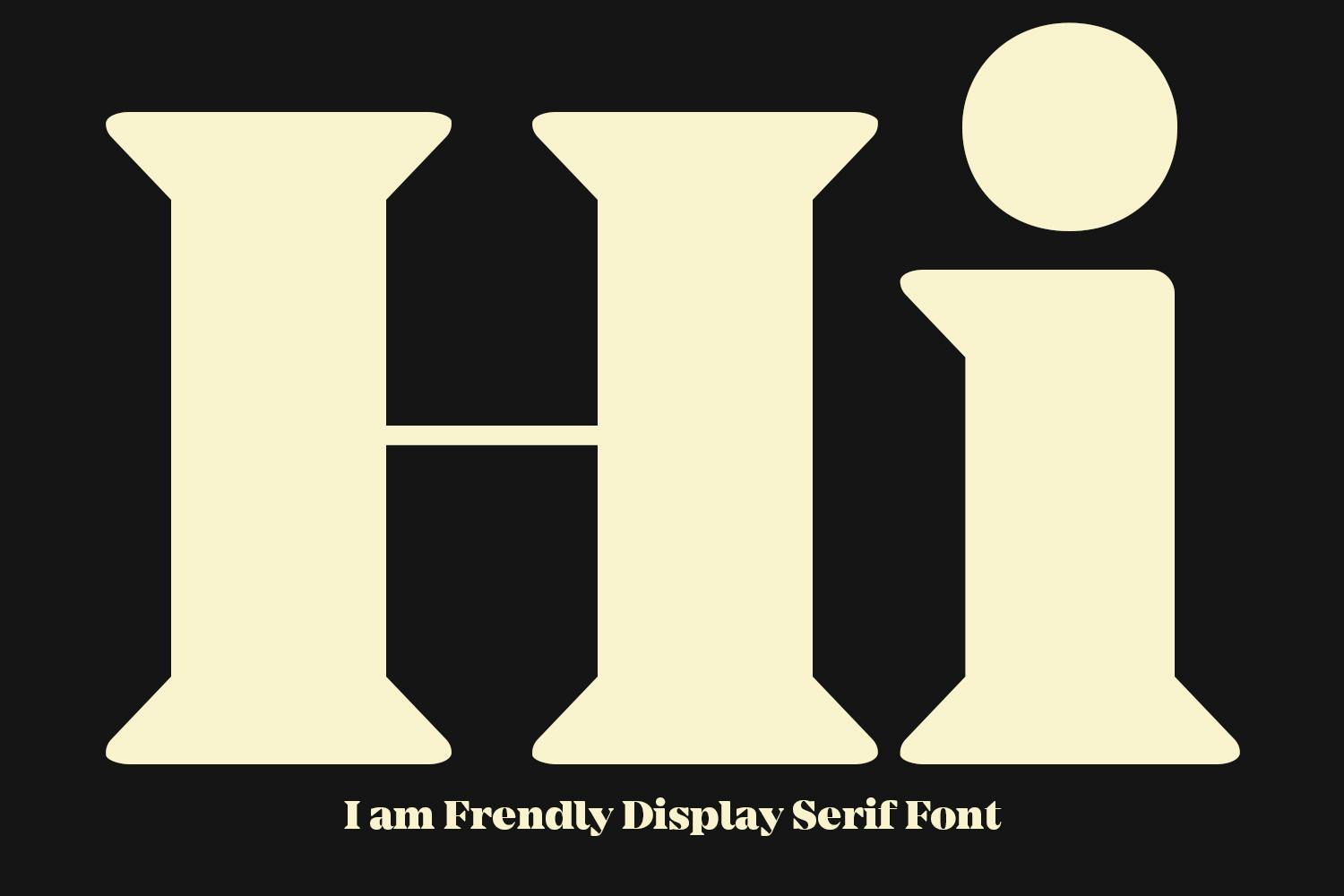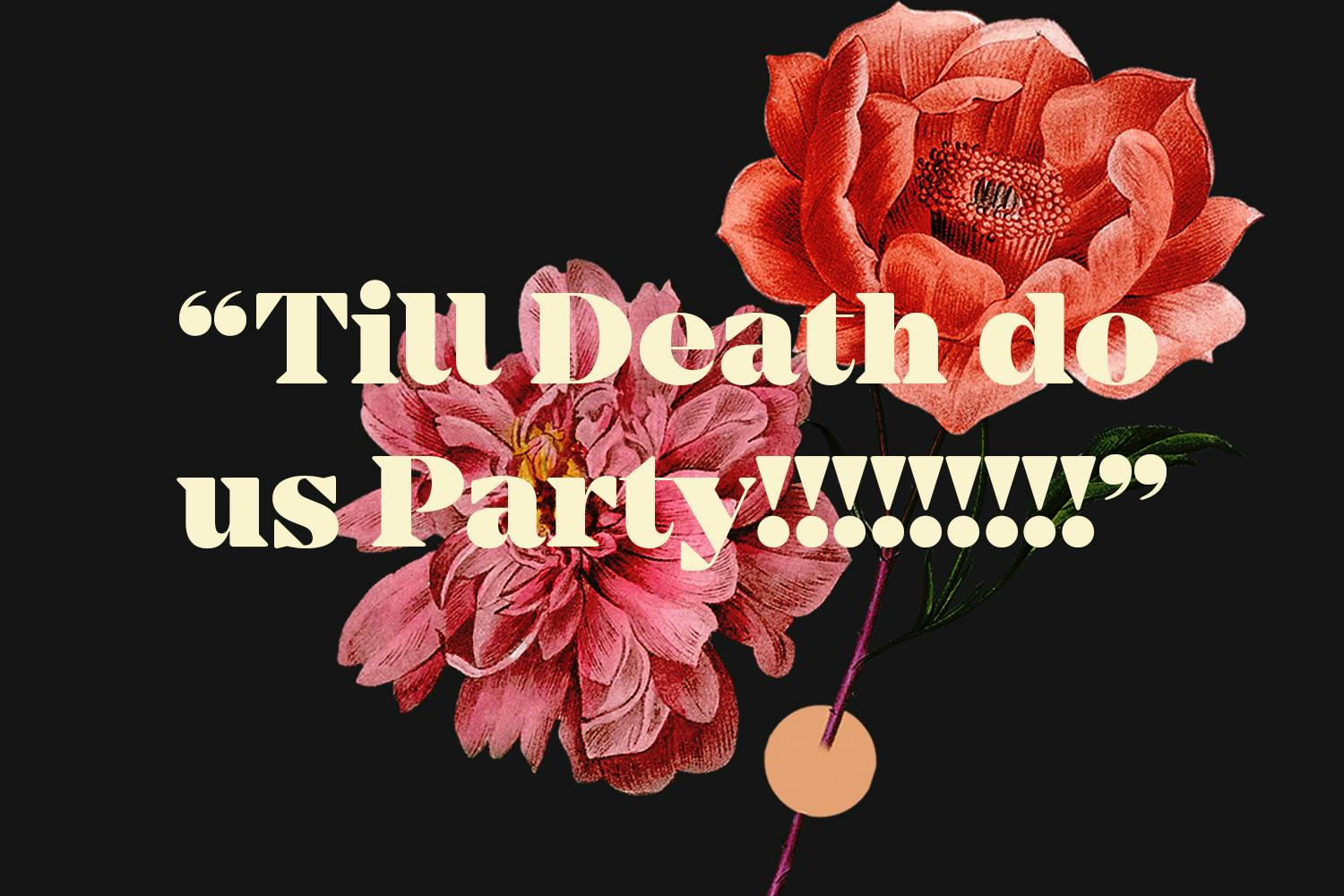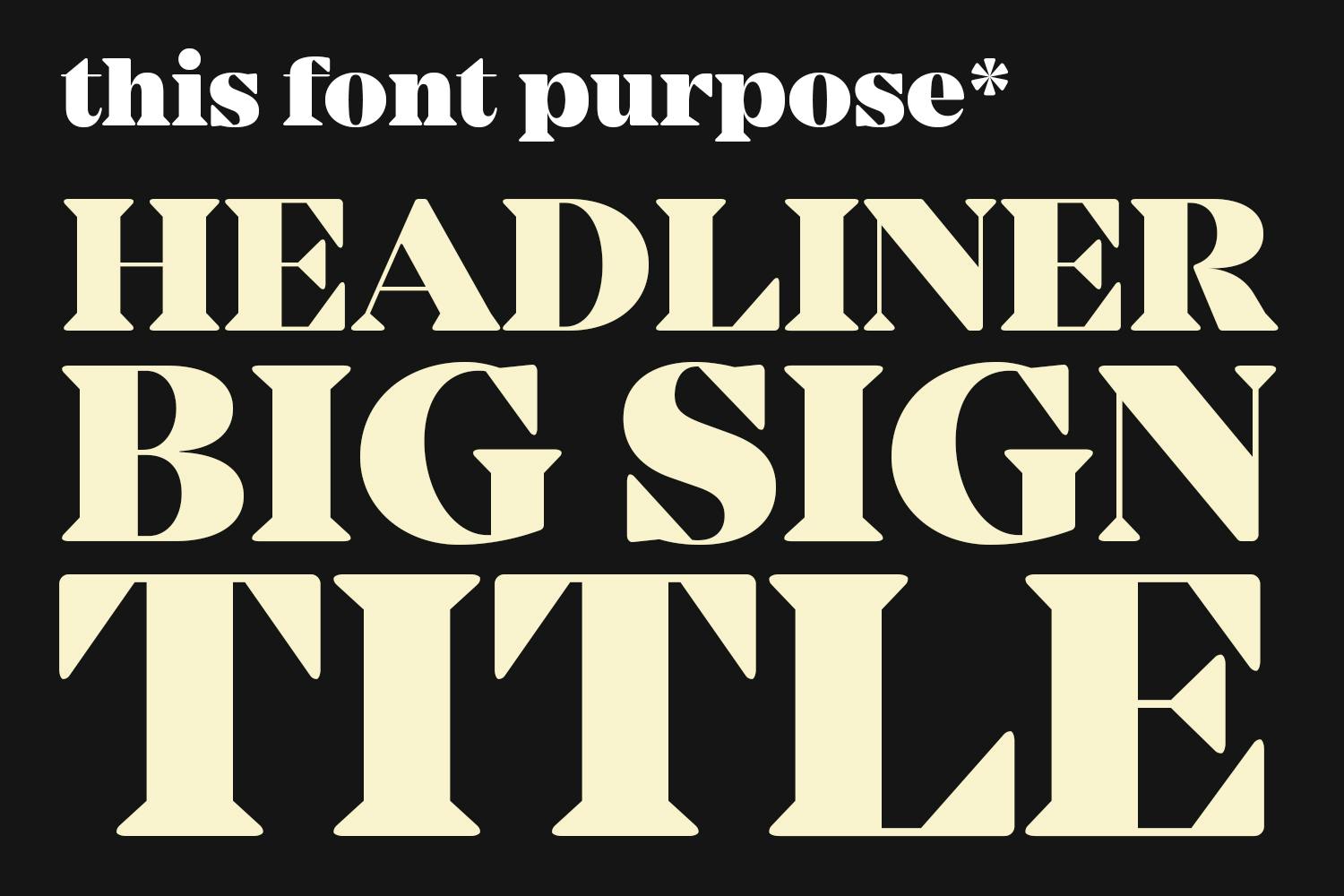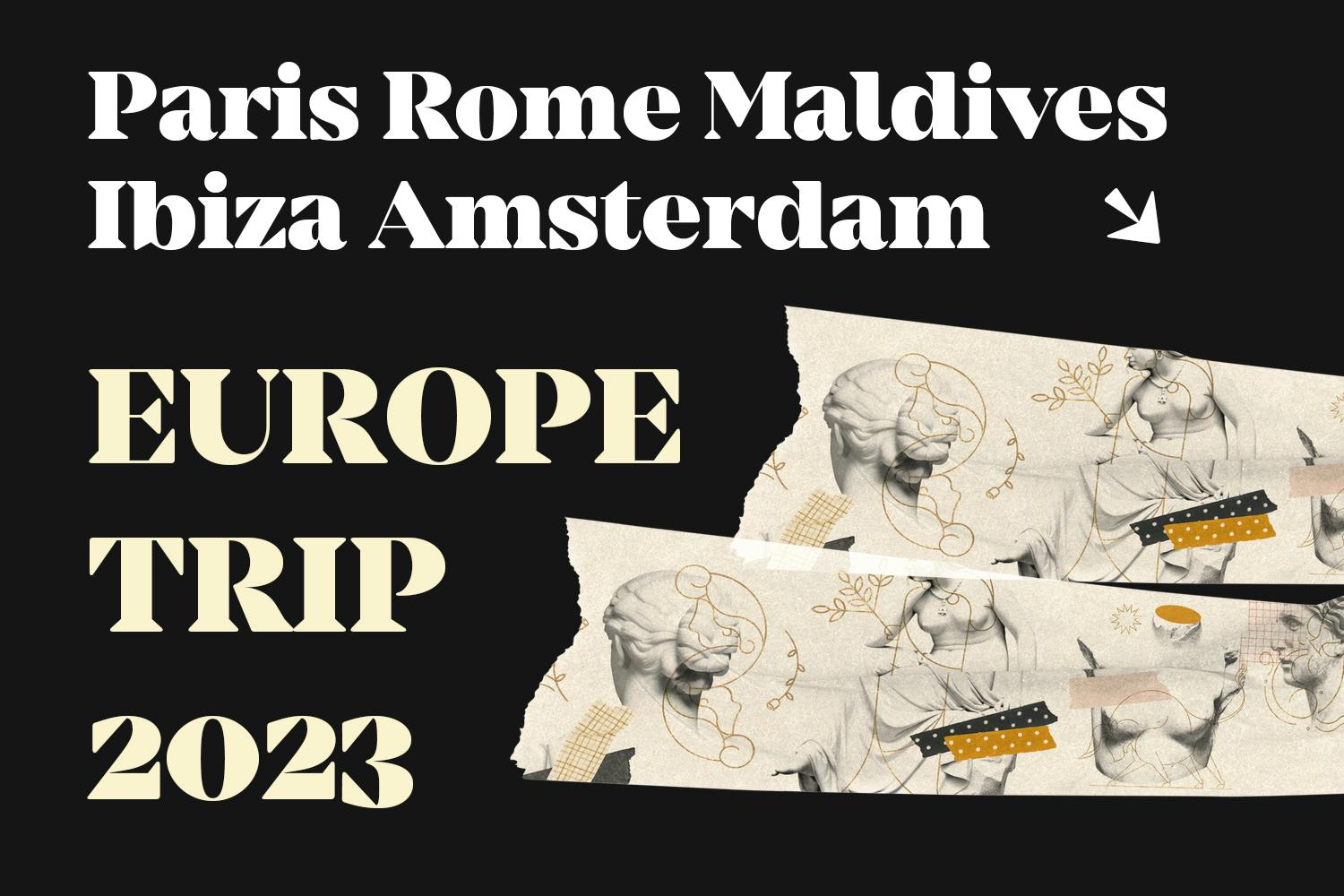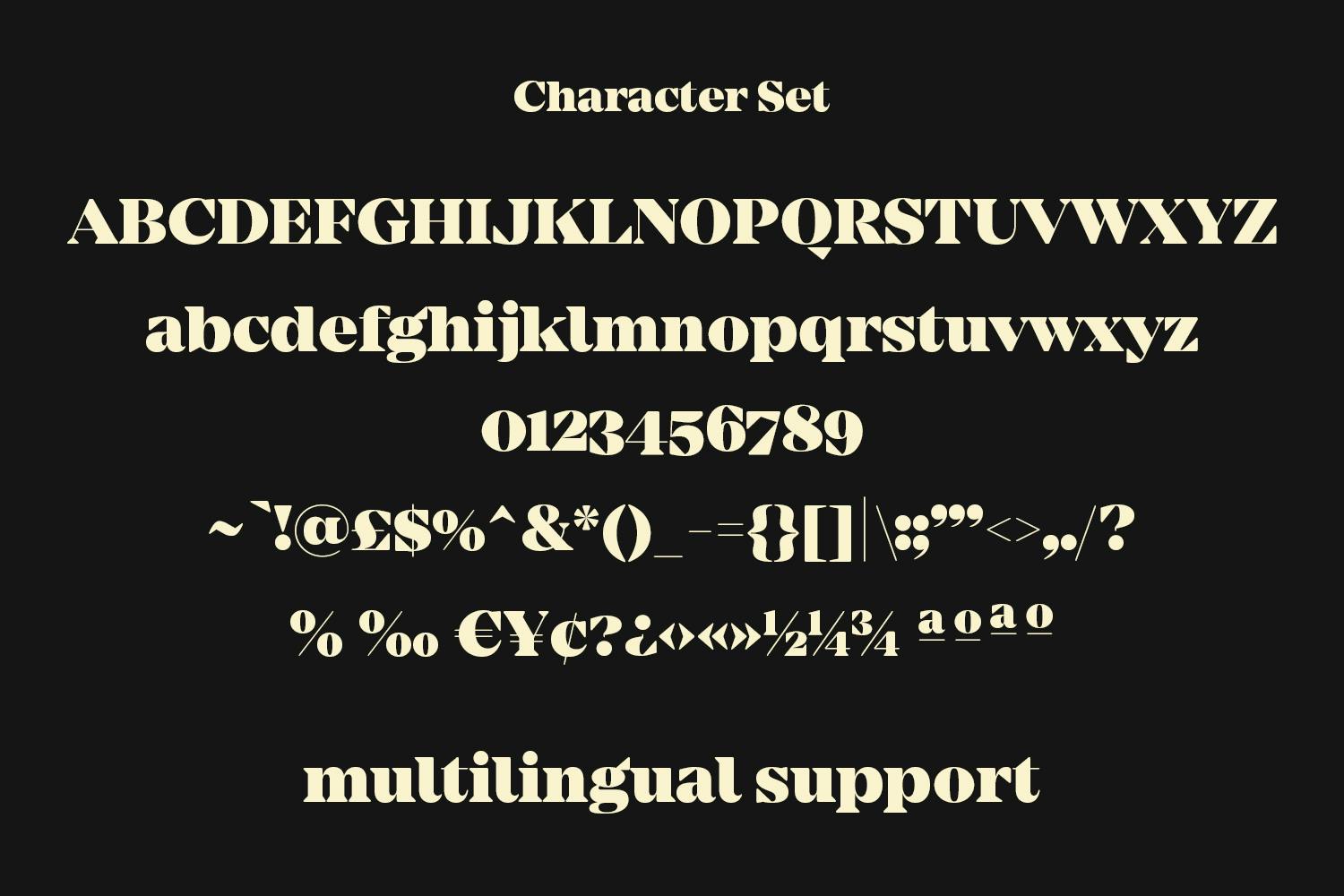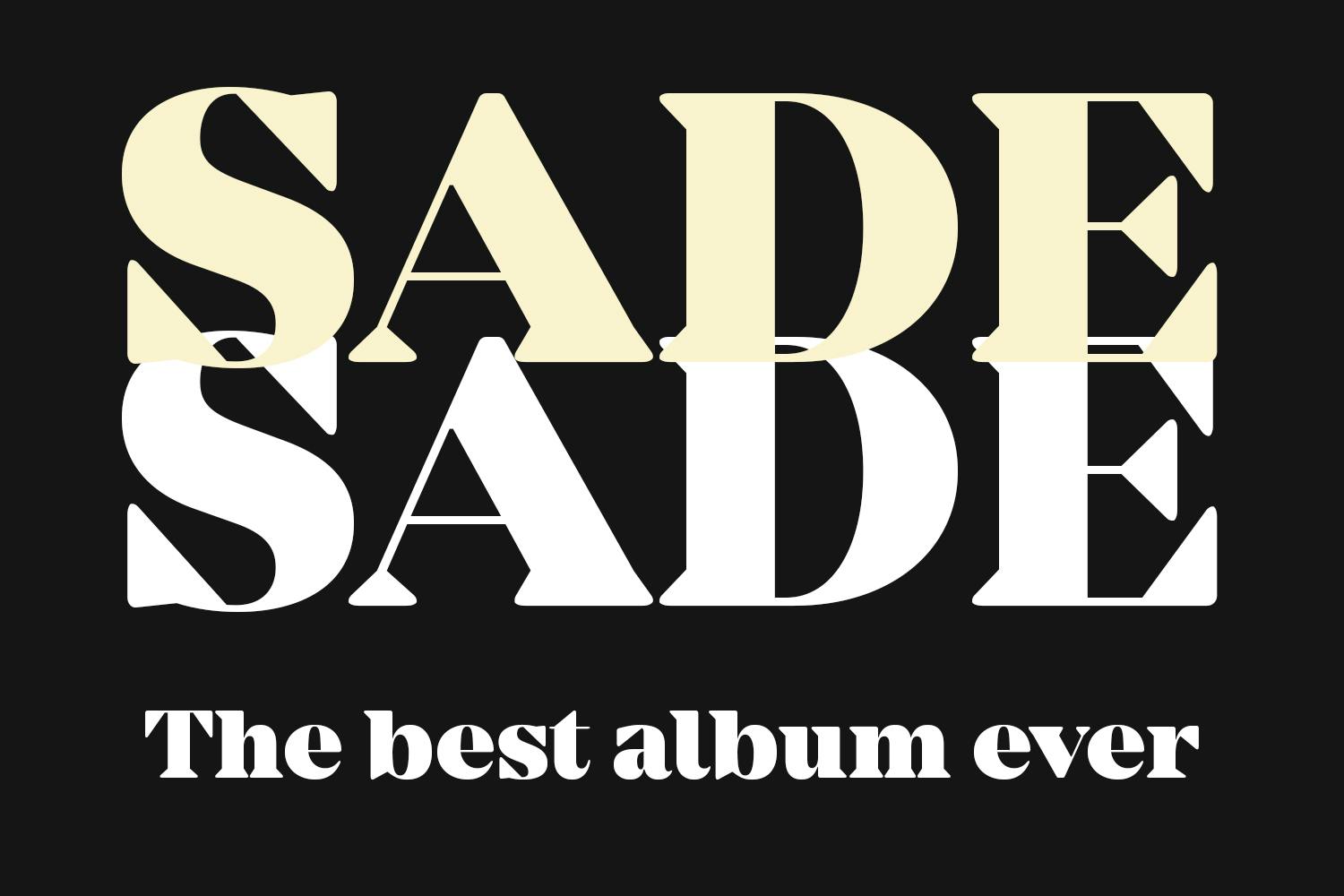
فونت Hatrok یک فونت سیرف مدرن و بولد است که به عنوان یک نمایشگر طراحی شده است. با کنتراست قوی، شخصیتهای جذاب و کمی لیگیچر و آلترناتیو، این فونت به شما کمک میکند تا کارهای خلاقانهتری انجام دهید. فونت Hatrok از بیش از ۱۰۰ زبان مختلف پشتیبانی میکند. این فونت برای طراحی لوگو، شبکههای اجتماعی، عناوین فیلم، عناوین کتاب، متنهای کوتاه و حتی نامههای بلند مناسب است و میتواند به عنوان فونت ثانویه شما در کنار فونتهای سنس یا سیرف استفاده شود. با فونت Hatrok، آثار خیرهکنندهای خلق کنید.